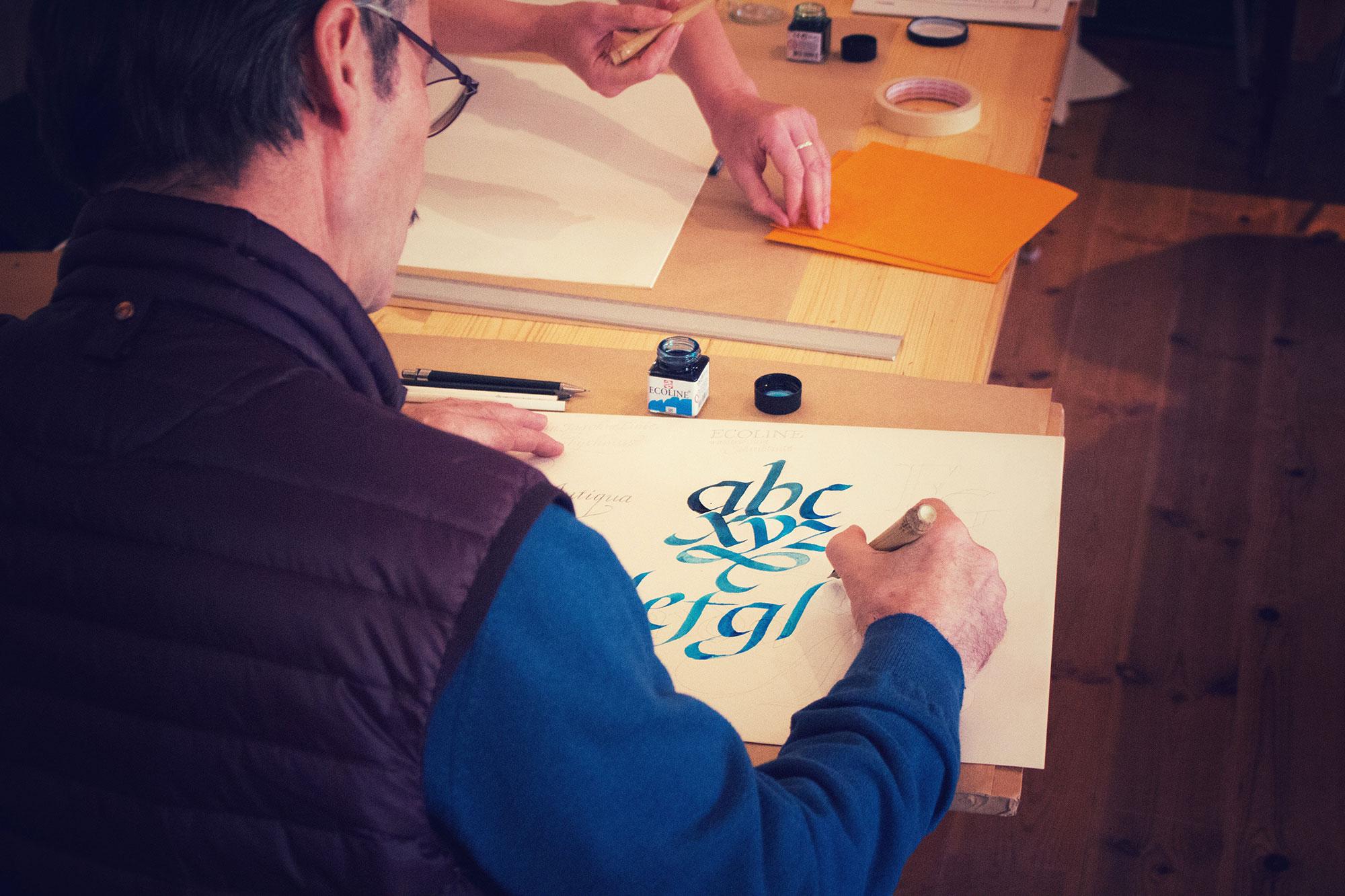
Ohne Wurzeln keine Flügel. Dieser dreiteilige Kalligrafie-Kurs mit Tobias-David Albert baut von sich von einer Renaissance-Kursiven oder Italic über das Schreiben von englischer Schreibschrift bis hin zu amerikanischen Brushscript-Schriften auf. Alle drei Kurse sind so angelegt, dass sie auch ohne die Teilnahme an den anderen beiden möglich sind.
Das zweite Wochenende steht im Zeichen der Spitzfeder. Anglaise, Copperplate oder formalere Spitzfederkursiven werden in kleinen Formaten probiert. Es gibt einen Überblick über die unterschiedlichen Qualitäten von Spitzfedern, Kronenfedern, Ellenbogenfedern u. a.. Dabei sind auch die unterschiedlichen Qualitäten vonTinten, Tuschen und Papieren wichtig. Die eleganten und zerbrechlichen Copperplate-Schriften verlangen eine hohe Kontrolle vom Schreiber und sind leichter verständlich durch die vorangegangene Basis der Breitfeder Kursiv.